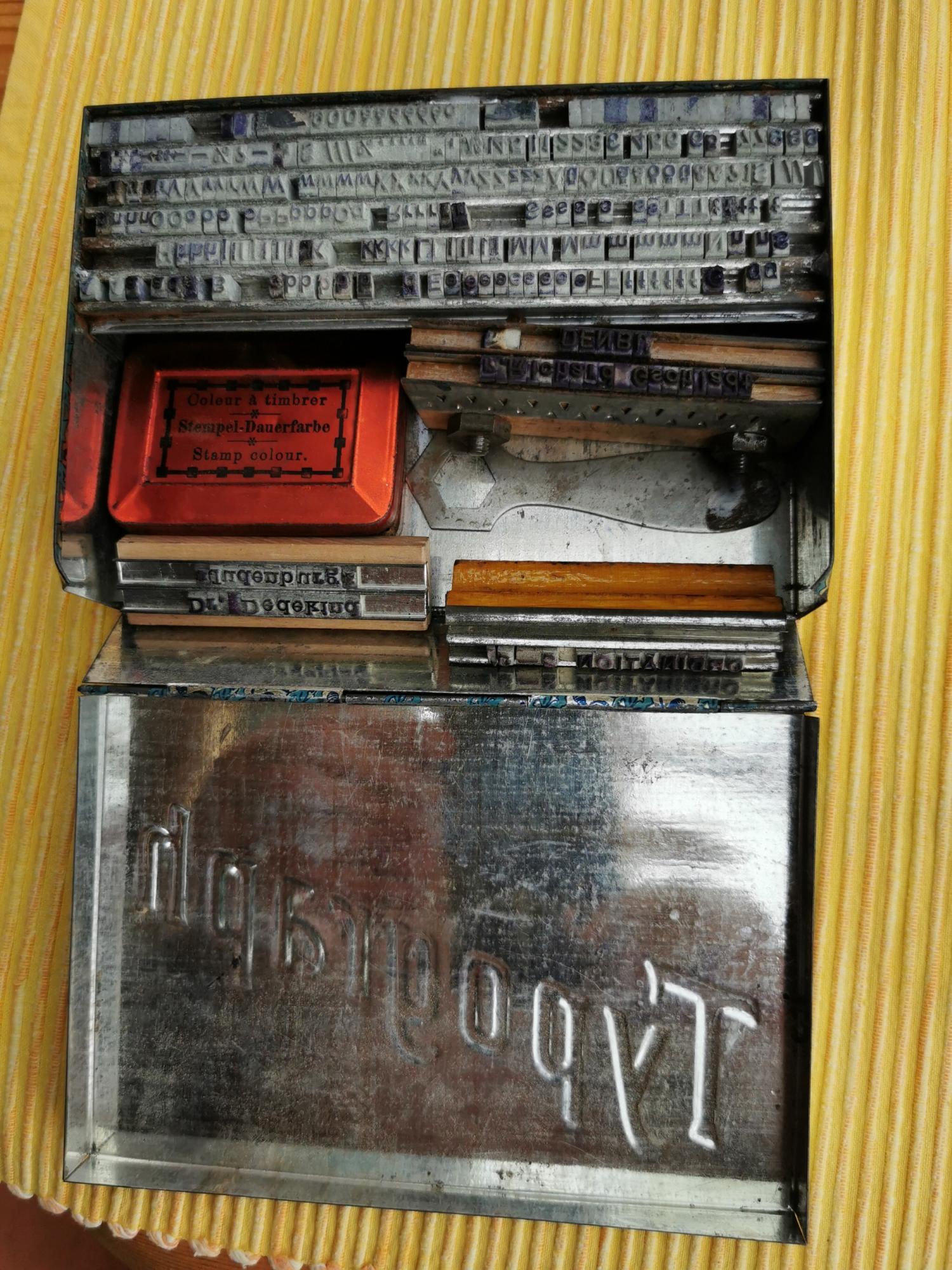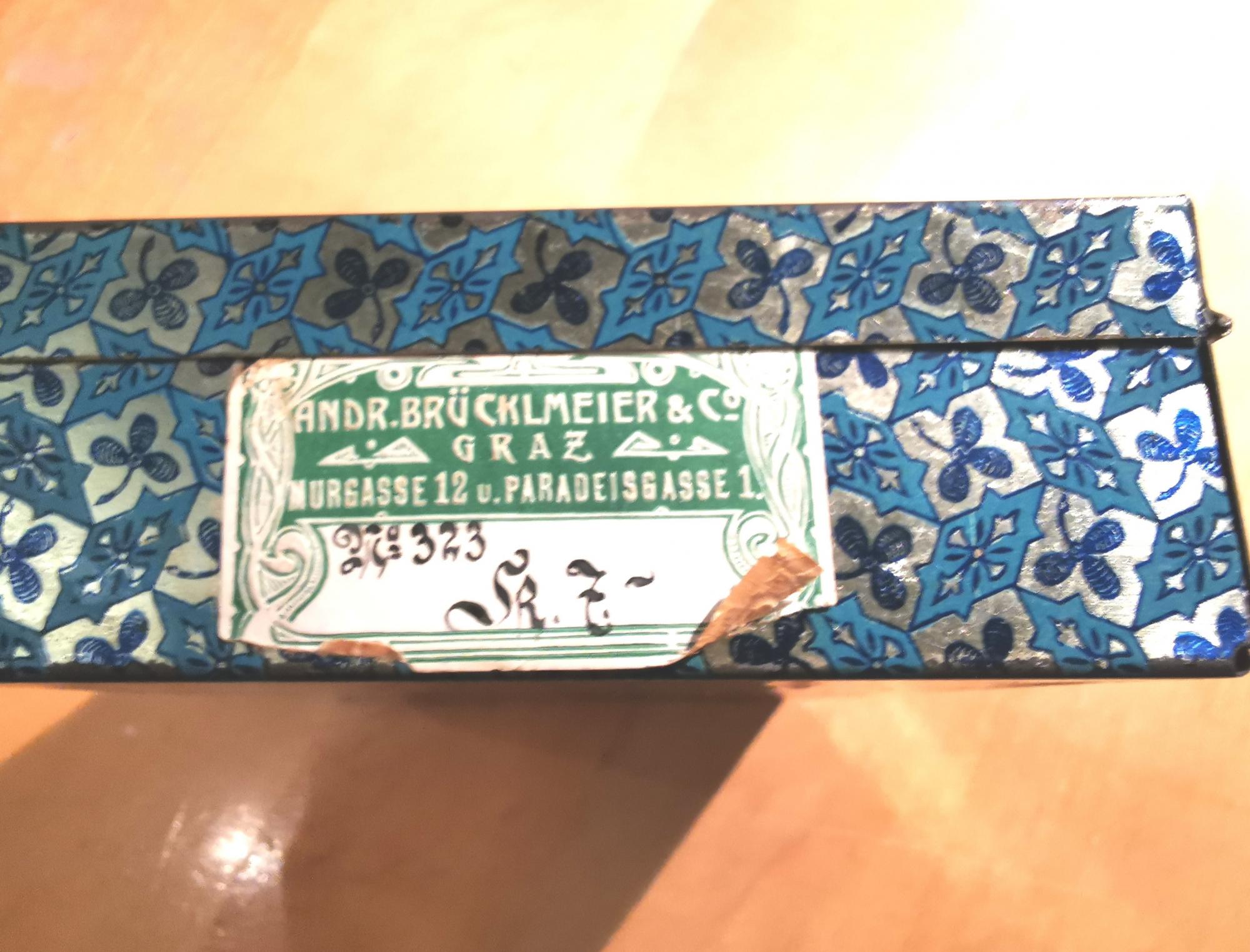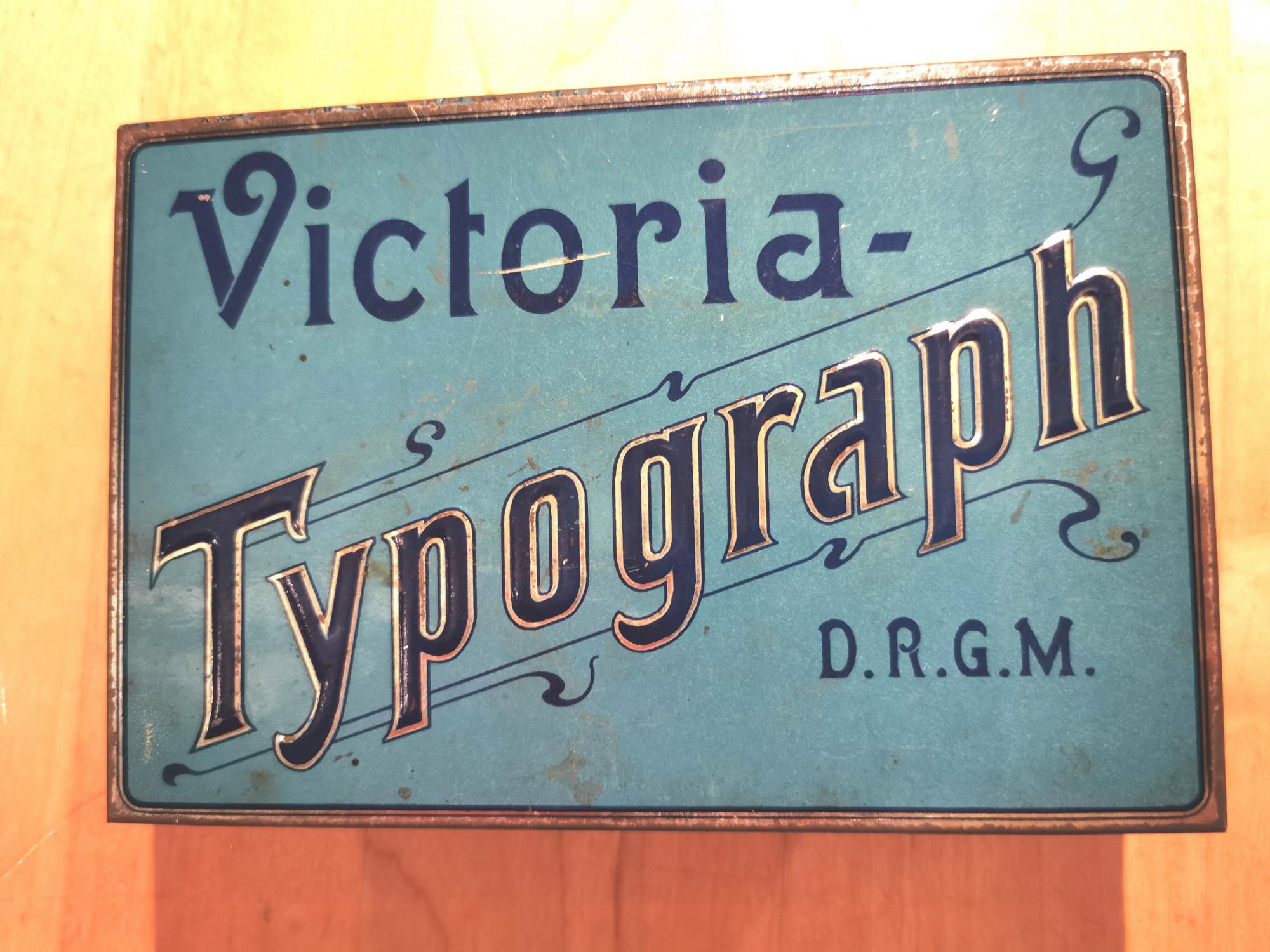
Blechdose mit Inhalt zum Stempeln
Wir haben beim Aufräumen des Archivs unserer zukünftigen Bleisatzschriften diese wunderschöne Blechdose mit Stempellettern und Zubehör gefunden - nun wüssten wir gern mehr darüber... vor allem das ungefähre Alter.
Wiki sagt: Der Musterschutz D.R.G.M. kam 1891 auf, mit Kronen zahlte man in Österreich bis 1925.
Das passt  doch  ganz gut zur Jugendstil-Gestaltung von Verpackung und Preisschild. Wenn ihr Glück habt, stammt der Karton aus der ersten Dekade des 20. Jahrhunderts.
Edit: Die Victoria-Sets, die man im Netz findet, sind aus den 30er-Jahren und später und sehen auch schon ganz anders aus ;-)
Nochmal Edit: Der Hersteller hieß Famos (gegr. 1891 in Leipzig)
ja, den Grazer Brücklmeier hab auch auch gefunden, aber keine weitere Historie dazu, deswegen hab ich hier gefragt, ob jemand was dazu sagen kann.
Merkwürdig finde ich schon, dass unter dem Suchbegriff "Victoria Typograph" mehrere verschiedene Dosen-Designs gezeigt werden, aber ALLE aus den 30er Jahren sein sollen ...
Das Produkt »Victoria Typograph« scheint recht erfolgreich gewesen und immer wieder aufgelegt worden zu sein. Ich hatte sogar den Eindruck, als hätte es auch noch eine größere Ausgabe »eurer« Visitenkarten-/Kinder-Druckerei gegeben.
Den Angaben der meisten Einsteller (meist irgendwelche Ebay-Angebote) ist leider nicht zu trauen. Ich habe selbst die Jugendstildose (!) bei einem kanadischen Militariahändler als »Nazi-Wehrmacht-SS« 40er-Jahre Feldpostdruckerei für Propaganda (Hersteller: DRGM) gefunden. Das ist so bescheuert, das kann man sich nicht ausdenken. Das Angebot ist natürlich auf  nordamerikanische  (unterbelichtete) WWII-Fetischisten ausgerichtet – die Zielgruppe ist leider größer als die der friedlichen Typo-Nerds.
Ich habe übrigens auch ein paar Bilder von Sets mit historistischer Gestaltung gefunden, die dürften eventuell also noch früher sein als das eure.